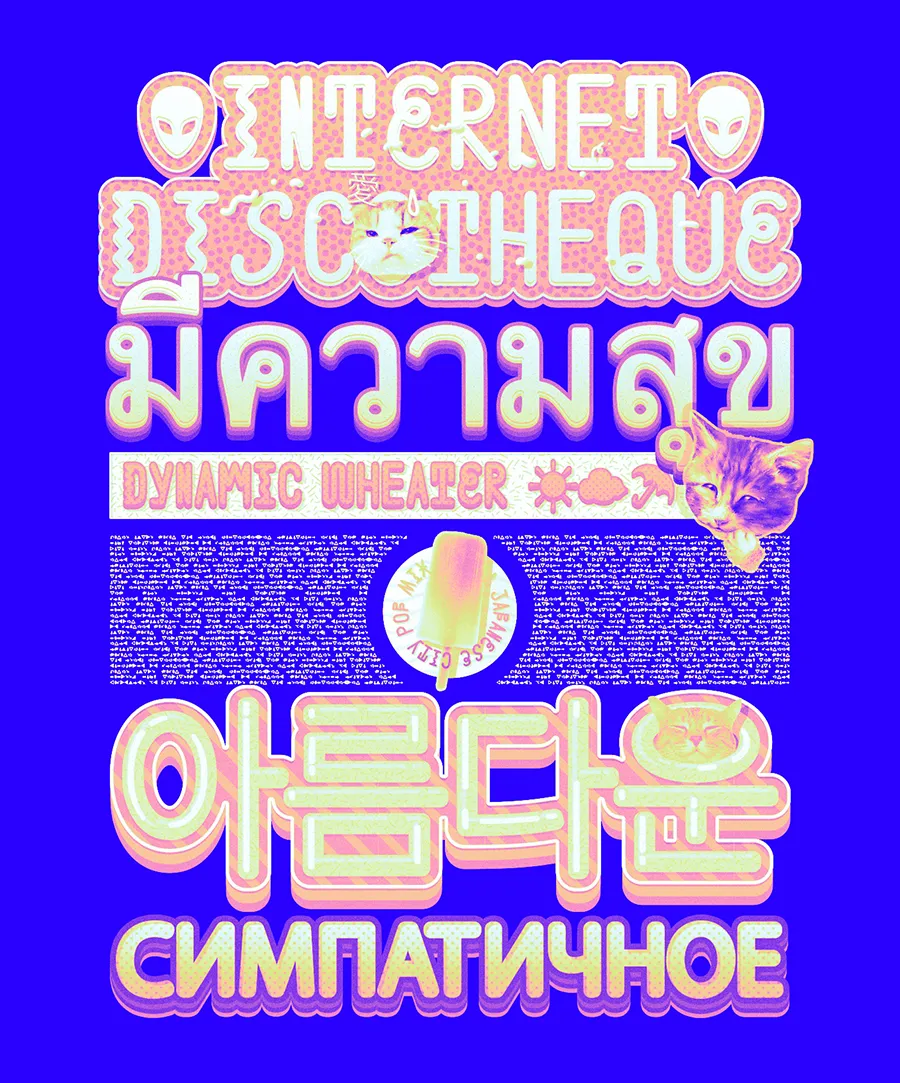
A fonte SODA POPP é uma criação inspirada na cultura pop, música vaporwave e seapunk que ganhou popularidade nos anos 2010 entre comunidades online. Inspirada no entusiasmo nostálgico pela estética cultural retro dos anos 80, 90 e início/mín dia 2000, esta fonte de estilo display carrega o poder vibrante da cultura pop contemporânea em sua essência. SODA POPP oferece um tom vibrante que transmite energia e frescor à cada letra. Ideal para designs onde deseja-se destacar a expressão visual, como marcas ou logotipos, esta fonte é certamente um destaque entre as demais. Inspirada em elementos da cultura pop, vaporwave e seapunk, SODA POPP mantém o espírito de uma fonte display moderna, mas também permite que os criadores busquem conexões com a era nostálgica dos anos 80 e 90. Uma verdadeira janela para a cultura pop contemporânea, essa fonte é certamente um elemento atraente em qualquer projeto visual que se destine a capturar o espírito vibrante do nosso tempo.